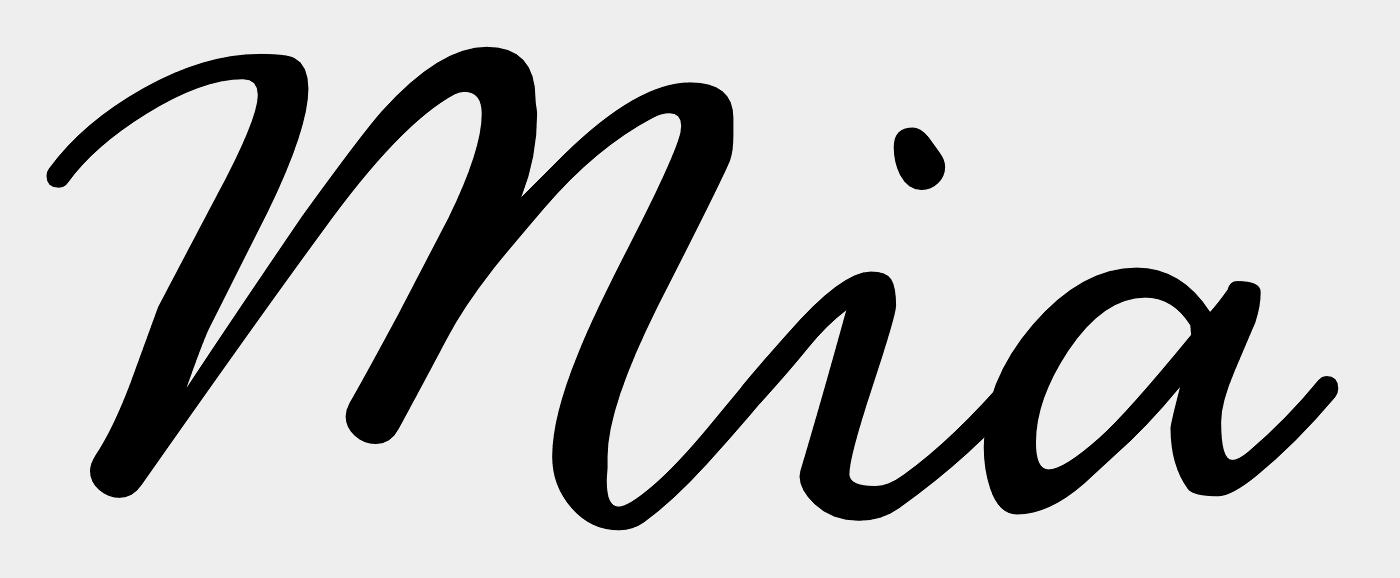
Suche Schriftart dieses ausschnittes des Logos einer Baguetteria
Inh. der Rechte: Baguetteria MIA
vermutete Entstehungszeit der Drucksache: vor ca 3 Jahren.
Kurze Erläuterung.
Die Rechtinhaberin hat mich bei der Modernisierung des Logos um Hilfe gebeten. Leider besteht jedoch kein Kontakt mehr zu dem Ersteller (Dieser ignoriert seid nun mehr  3 Jahren Ihre Anfragen). Daher ist es auch nicht ganz klar, ob der Schriftzug selbst erstellt wurde oder aber eine Satzschrift verwendet wurde.
Das sieht handgemacht aus. Bei einer Satzschrift wären die Anschlüsse auf einer Linie und mit ähnlichen Steigungen.
Dies habe ich mir auch schon fast gedacht.
Kenen Sie vielleicht eine Schriftart (Satzschrift), die dieser ähnlich ist? Kann auch was kosten.
Das M ist schon sehr speziell … vielleicht in diese Richtung?